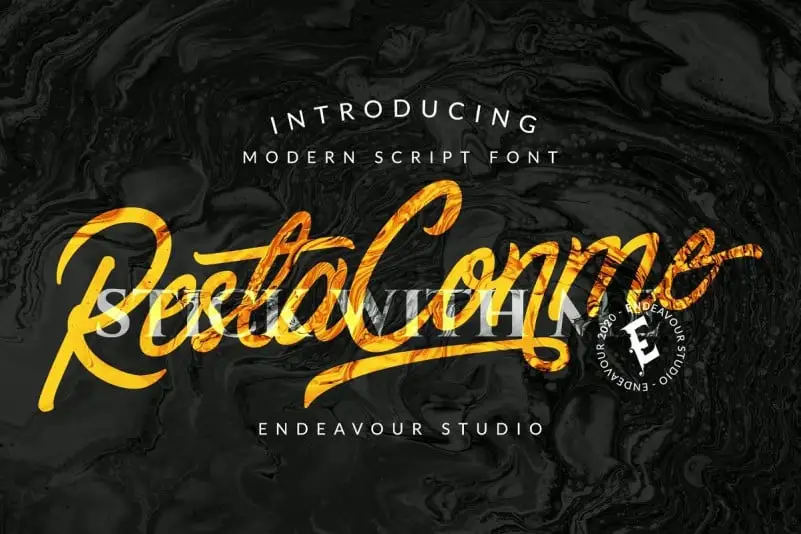
Restaconme Script Font – Download Grátis
A Restaconme Script Font é uma beleza em tipo script com alternativas de caracteres cursivos adoráveis. Desenvolvida por Endeavour Studio na categoria de fontes de tipo script, esta opção moderna inspira-se no estilo de letra à mão para o nome e vem do gosto delicado do pianista italiano Ludovico Einaudi. Perfeita para projetos criativos envolvendo roupas, camisetas, logotipos, casamentos, convites, cartões, embalagens de produtos, cabeçalhos, logotípicas, etiquetas e até mesmo desenhos de roupa. Ideal para quem busca adicionar um toque único a seus projetos digitais ou impressos. Em um mundo onde a criatividade é a chave do sucesso, esta fonte é uma excelente adição à sua coleção.